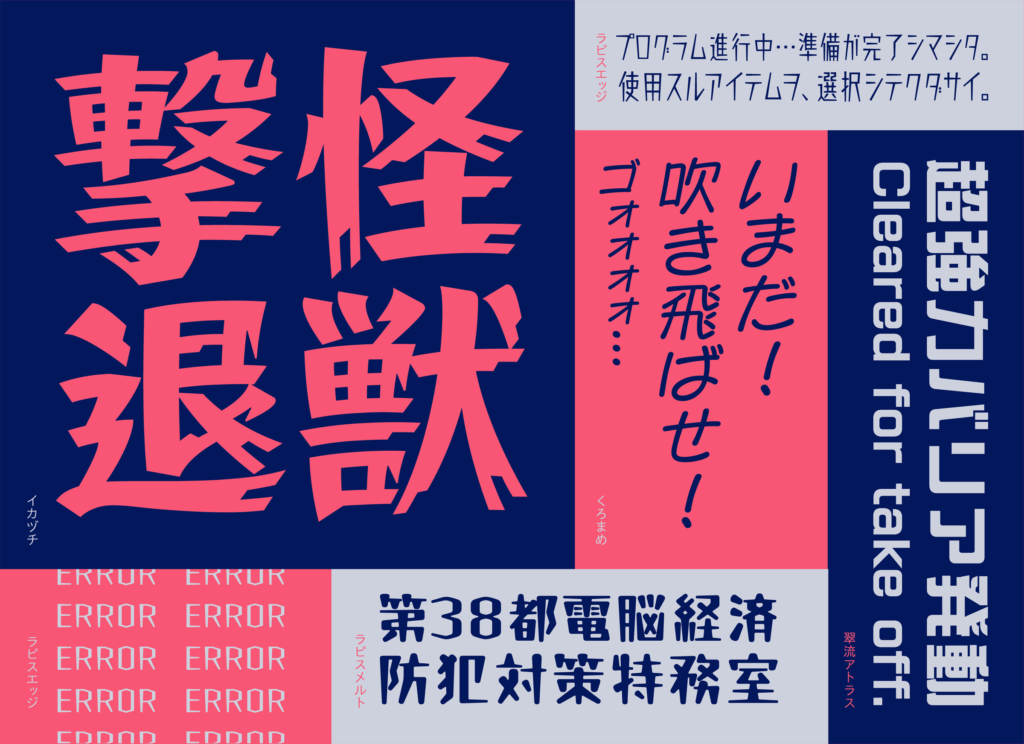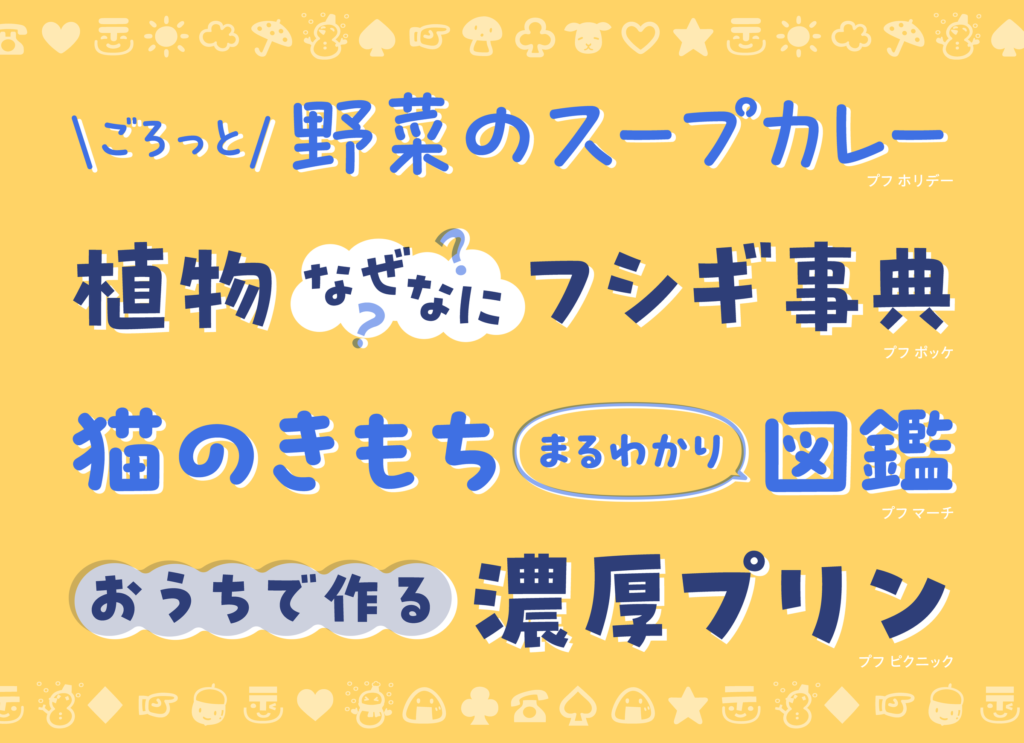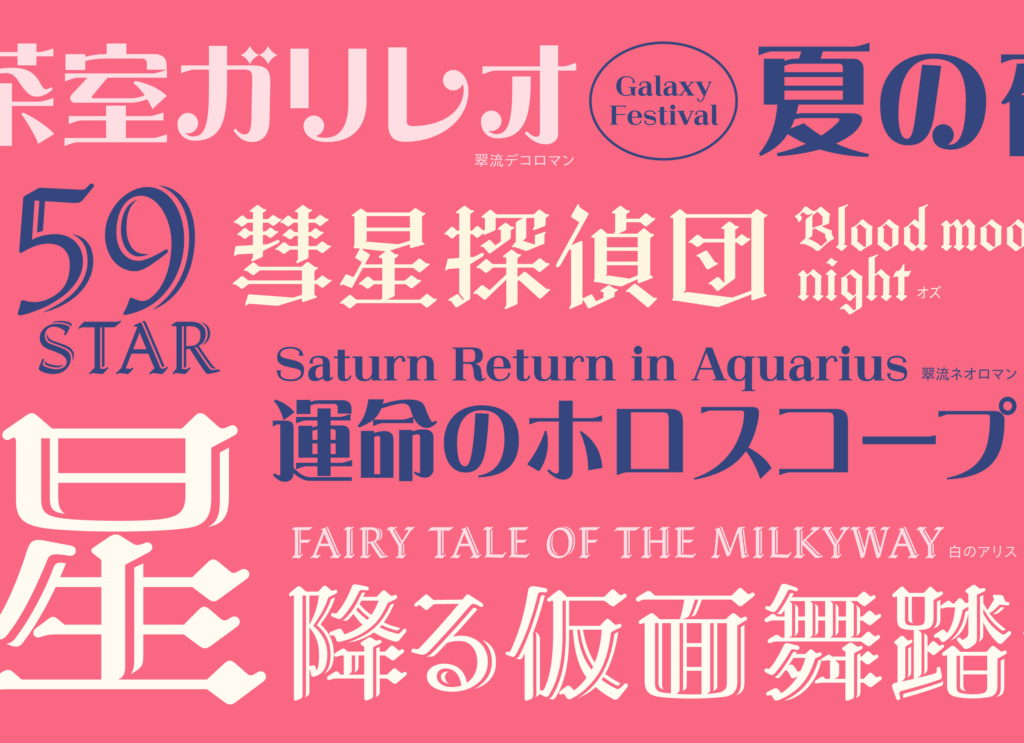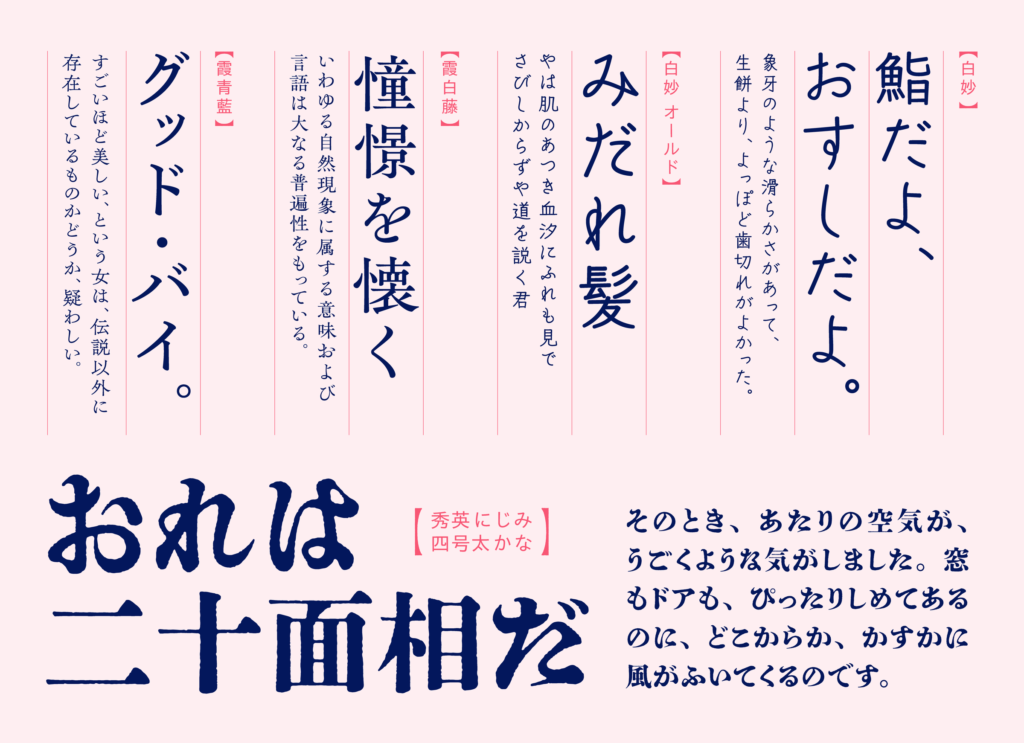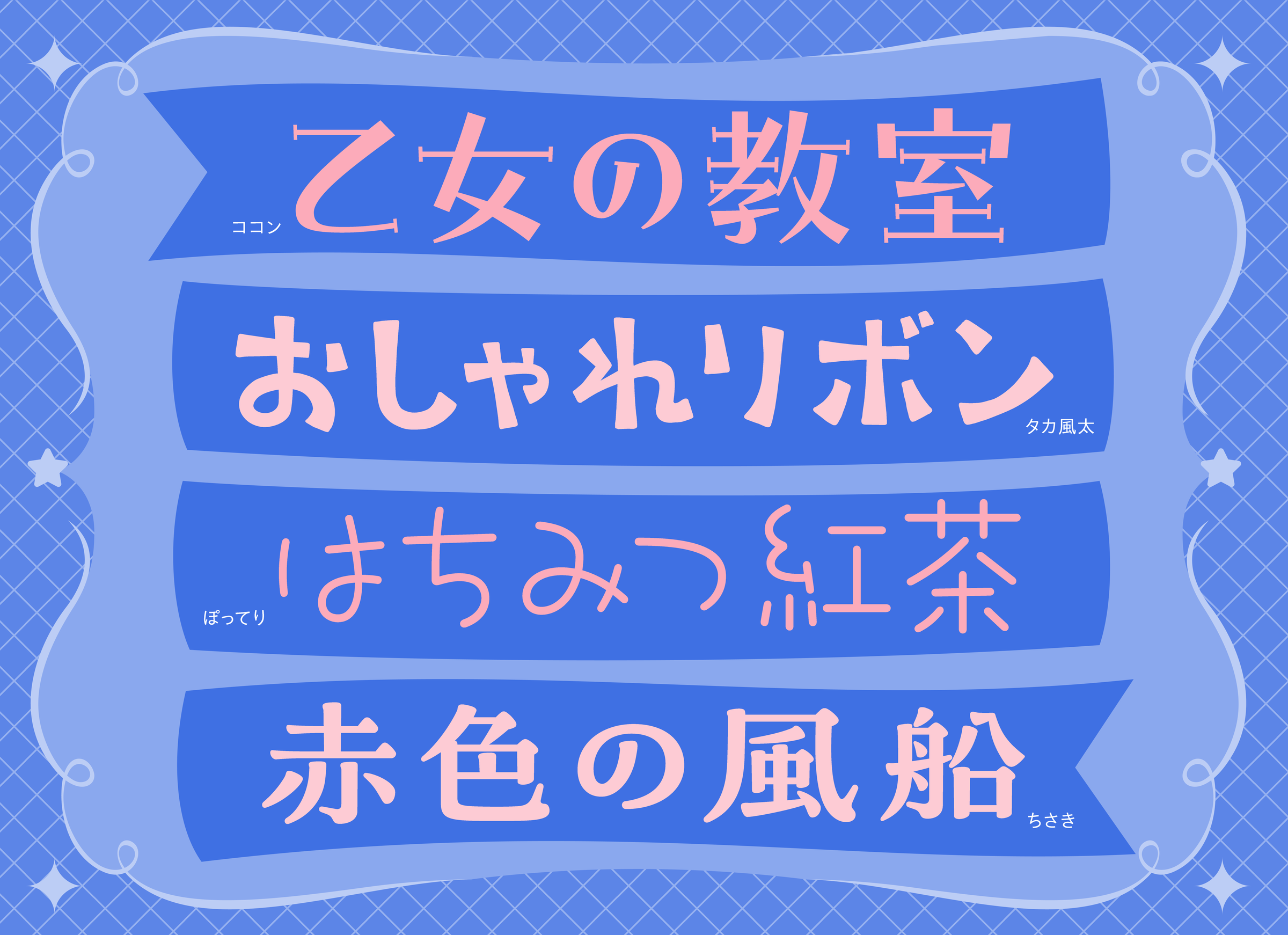
モリサワ デザイン書体などを大幅拡充 『インパクト』『ゆるポップ』『ロマン』『オールド』の4ジャンル
株式会社モリサワは、 2022年秋にリリースする新書体において『インパクト』『ゆるポップ』『ロマン』『オールド』の4つのジャンルでデザイン書体などを強化する。
近年、 オンスクリーンでのコミュニケーションが活発化している背景を受け、 特定の印象や世界観の演出に効果的な和文デザイン書体を一挙に充実させることで、 より表情豊かな文字表現を可能にする。
追加する和文デザイン書体などのジャンル名は、 書体の持つ雰囲気や利用シーンをイメージしている。
字面が大きめで迫力を感じさせる書体が揃う『インパクト』、 あどけなさや遊び心を感じさせる書体が揃う『ゆるポップ』、 個性的な装飾を取り入れたレトロ可愛い書体が揃う『ロマン』、 筆や活字の雰囲気を残したクラシカルな印象の書体が揃う『オールド』の4つ。 これらの書体25ファミリーは、 2022年秋の提供を予定している。
ジャンル① 大胆な『インパクト』を与える書体
『インパクト』のジャンルは、 雷鳴で割れたような端々の装飾がパワフルな迫力を与える書体「イカヅチ」や、 直線で構成されたシンプルな設計でありつつ独特の印象を与える書体「ラピスエッジ」「ラピスメルト」など5ファミリー。 ゲームやコミックなどをはじめ、 コンテンツの世界観を演出するシーンで使いやすいラインナップ。
ジャンル② 遊び心のある『ゆるポップ』な書体
『ゆるポップ』のジャンルは、 低い重心とやや下にすぼまるプロポーションを持つ、 レトロであどけない雰囲気の書体「ココン」や、 筆ペンで書いた文字をイメージしたゆる可愛い書体「ぽってり」のほか、 「プフ ピクニック」「プフ ホリデー」といった統一しすぎない自由な字形と小さめの字面が特徴の「プフ」シリーズなど、 8ファミリー。 親しみやすさや柔らかい印象を与えたい場面におすすめのラインナップ。
ジャンル(3) レトロ可愛い『ロマン』な書体
『ロマン』のジャンルは、 やや低めの重心をもつスクエアな骨格の漢字を共通とした、 ハイコントラストな書体「翠流ネオロマン(すいりゅうねおろまん)」「翠流デコロマン(すいりゅうでころまん)」のほか、 人気のかな書体に漢字を追加した書体「白のアリス」「オズ」の4ファミリー。 エレメントなどに個性的な装飾が取り入れられており、 ひと目見ただけでレトロかつ華やかな印象を与えるラインナップ。
ジャンル(4) 細やかに機微を演出する『オールド』な書体
『オールド』のジャンルは、 楷書体や活字からインスパイアされたオールド系の明朝体「霞青藍(かすみせいらん)」「霞白藤(かすみしらふじ)」に加え、 手書き文字の優しい印象をもつペン字風のデザイン書体「白妙(しろたえ)」「白妙 オールド(しろたえ おーるど)」など8ファミリー。
おなじみの秀英にじみシリーズからは、 「秀英四号太かな」をベースに “にじみ” を再現した書体「秀英にじみ四号太かな」、 字游工房からは繊細なニュアンスの違いが楽しめる本文用書体「文游明朝体 古雅かな(ぶんゆうみんちょうたい こがかな)」「文游明朝体S 朝靄かな(ぶんゆうみんちょうたいえす あさもやかな)」「文游明朝体S 水面かな(ぶんゆうみんちょうたいえす みなもかな)」が仲間入りしている。